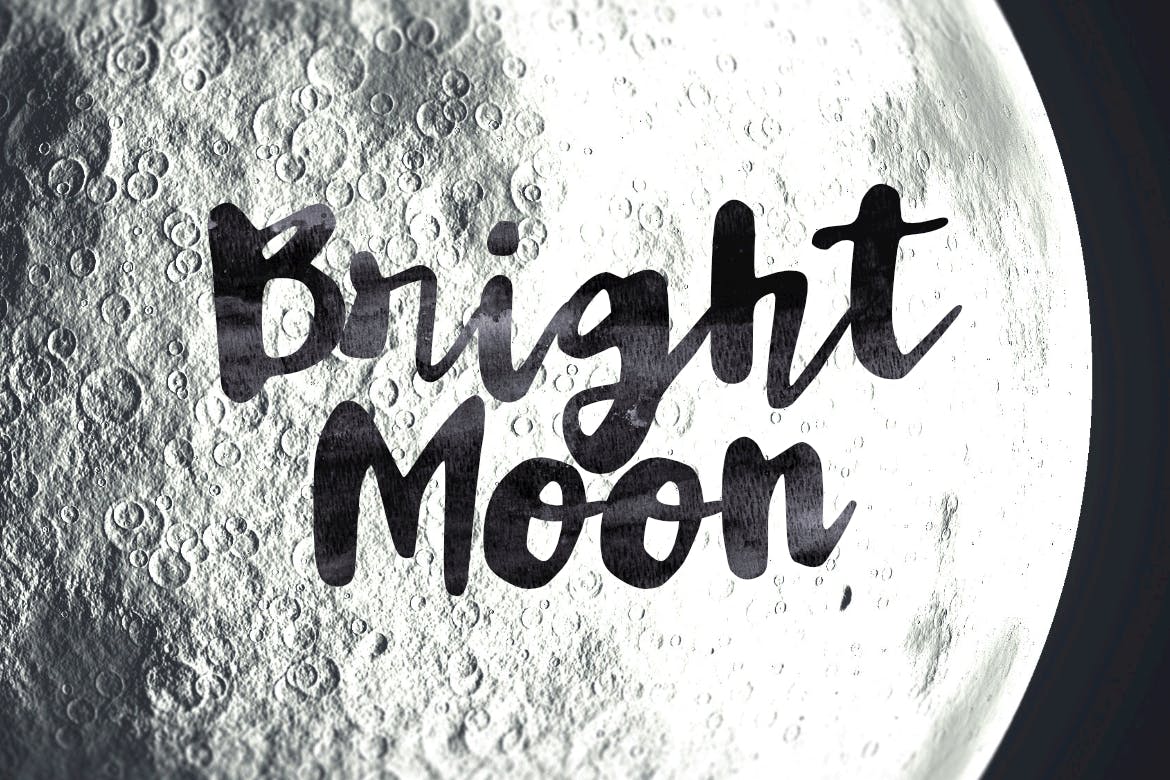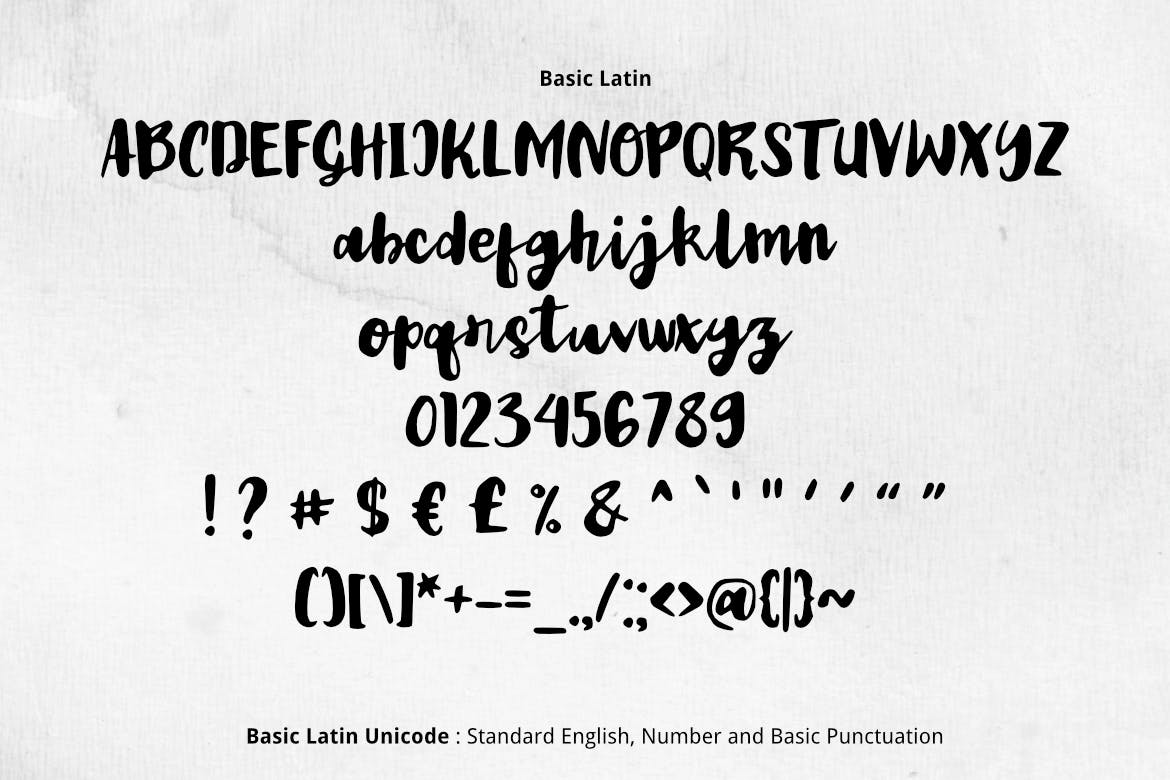
فونت وینتیج اینک
این فونت زیبا و چندمنظوره، با طراحی ساده و شیک، مناسب برای پروژههای مختلفی مانند کتابهای کودک، نقلقولها، لوگوها، عناوین و غیره است.
پشتیبانی از زبانهای پایه لاتین (کاراکترهای استاندارد انگلیسی، اعداد و نمادها).